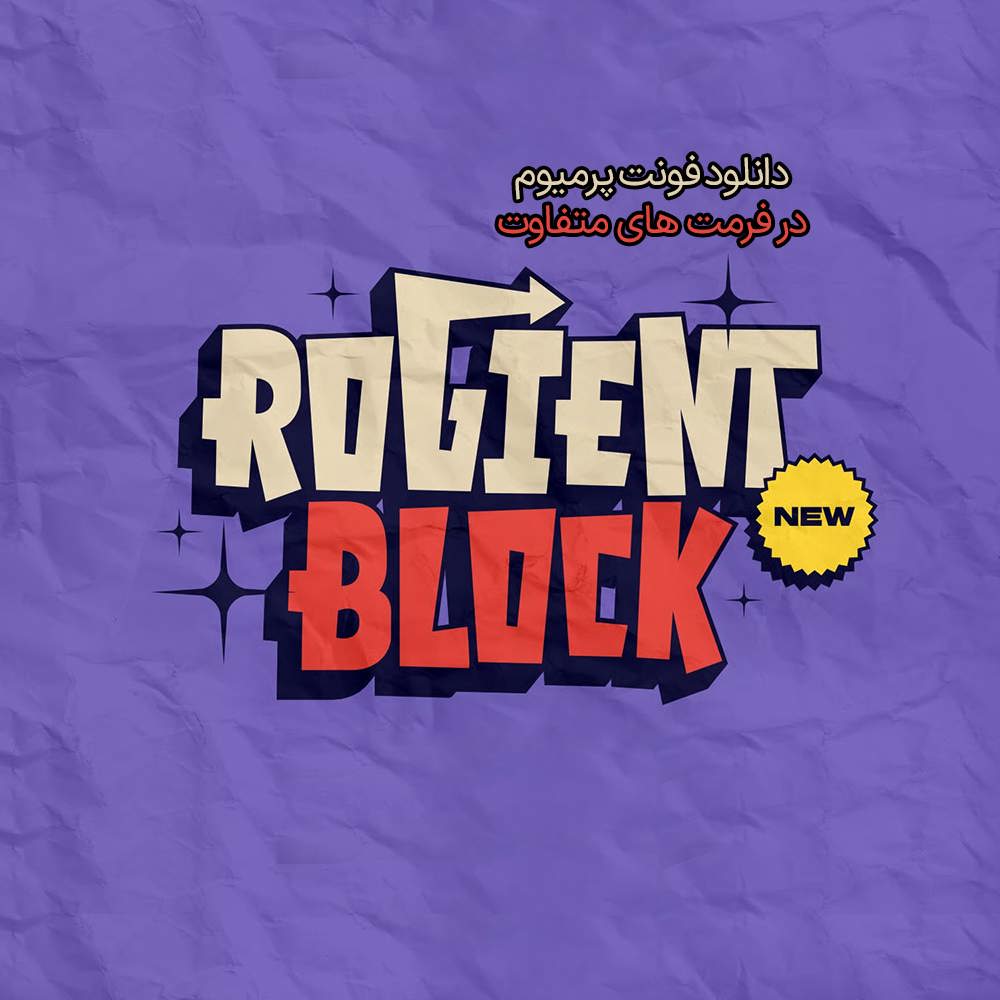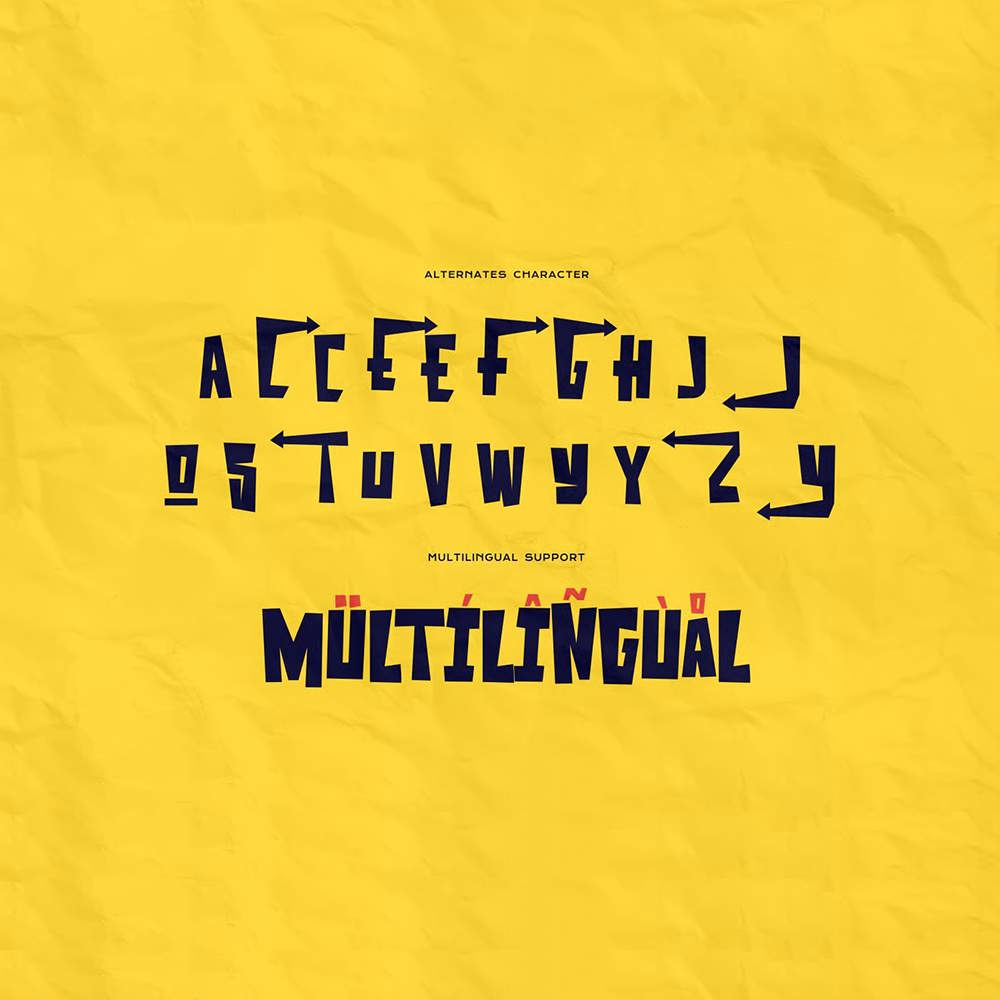
دانلود فونت انگلیسی Rogient Block Font
فونت پرمیوم و انگلیسی Rogient Block Font یک فونت نمایشی جسورانه و بلوکی است که از کمیک و پانک با زیباییشناسی سرگرمکننده الهام گرفته شده است. شکلهای حروف زاویهدار و نامنظم و جایگزینهای منحصر به فرد به سبک پیکان، احساسی سرگرمکننده و پرانرژی ایجاد میکنند. سبک بازیگوشانه و کمی تحریفشده آن، حس تند و تیز و پر جنب و جوش را افزایش میدهد و برای جلب توجه در ترکیبهای بصری پویا ایدهآل است. این فونت برای پوسترها، کالاها یا هر طرحی که به دنبال ظاهری جسورانه، عجیب و غریب و جذاب است، عالی است.